Althochdeutsch 900–1050
Aus dem 9. Jahrhundert sind insgesamt nur drei buchfüllende deutsche Texte erhalten — die deutsche Sprache betritt zaghaft die Bühne der Schrift.
So oder so ähnlich hätte eine Urkunde damals aussehen können. Das hier gezeigte Schreiben entstand 2016 auf der Wachsenburg und erhebt den Gaukler Laut’nHals in den Stand eines Diplom-Dummschwätzers. Der Schreiber, Michael Jacob Ritter de Fisch, war einer der wenigen, die diese alte Schrift ohne Linien mit einer Gänsefeder zu Papier bringen konnten.
Der althochdeutsche Tatian (St. Gallen, Stiftsbibliothek, Cod. Sang. 56) ist die erste bekannte Übersetzung der Evangelien in die deutsche Sprache. Vorlage war die in Latein geschriebene Evangelienharmonie des Tatianus aus dem 2. Jh.
Viele andere bekannte deutschsprachige Texte wurden lediglich an den Rand oder sogar auf die Rückseite anderer Texte geschrieben. Das bekannteste Beispiel ist wohl das Hildebrandlied — auf der Vorderseite des ersten und der Rückseite des letzten Blattes eines codex von ca. 830, der ansonsten lateinische Texte enthält. Aus Platzmangel ist es nur unvollständig überliefert.
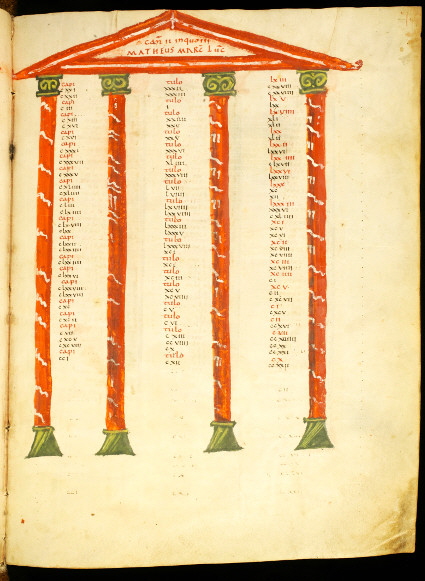
Um 900–1050
Erste deutsche Zeilen auf Pergament
Cod. Sang. 56, Evangelienharmonie des Tatian
St. Gallen, um 830
Der althochdeutsche Tatian
In der Schreibstube von St. Gallen entsteht die erste bekannte Übersetzung der Evangelien ins Deutsche. Auf dem aufgeschlagenen Pergament stehen Latein und Althochdeutsch nebeneinander — die junge Sprache lernt von der älteren, wie man Bücher macht.
Urkunde im Stil einer althochdeutschen Schrift
Nachempfunden, 2016
Eine Urkunde, wie sie ausgesehen haben könnte
So mag eine Urkunde des frühen Mittelalters gewirkt haben: dichte Buchstabenreihen ohne Linien, mit der Gänsefeder gesetzt. Michael Jacob Ritter de Fisch ließ auf der Wachsenburg den Gaukler Laut’nHals zum Diplom-Dummschwätzer aufsteigen — Augenzwinkern für eine ernsthafte Schrifttradition.
Hildebrandlied, erste Seite
Um 830, Fulda
Hildebrandlied — Anfang
Auf der Vorderseite des ersten Blattes eines lateinischen codex hat ein Schreiber das Hildebrandlied festgehalten. Die deutschen Verse drängen sich an den Rand des Pergaments — die Heldendichtung ist Beifang einer lateinischen Handschrift.
Hildebrandlied, zweite Seite
Rückseite, abrupt zu Ende
Hildebrandlied — Schluss
Auf der Rückseite des letzten Blattes endet das Lied mitten in der Geschichte: dem Schreiber ging schlicht das Papier aus. So bleibt einer der bedeutendsten Texte der deutschen Literaturgeschichte für immer ein Fragment.